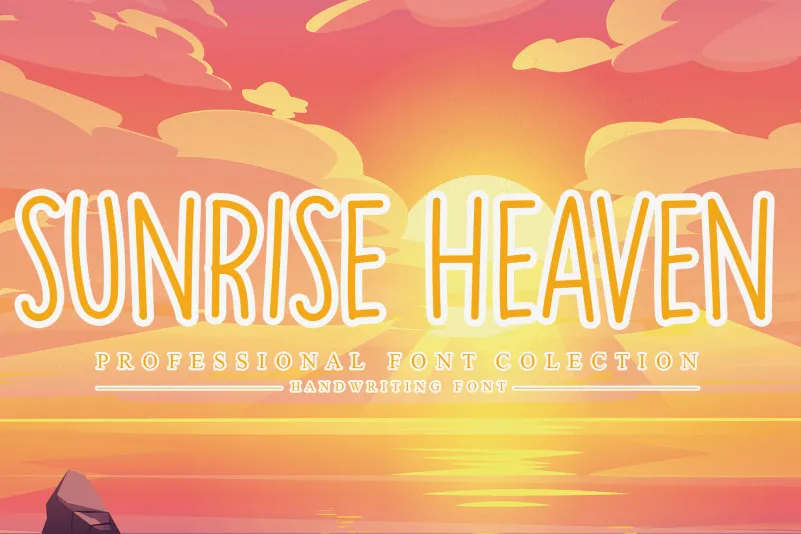
Sunrise Heaven Display Font – Fonte Grátis
Sunrise Heaven Display Font
A Sunrise Heaven Display Font é uma elegante fonte escrita a mão que se destaca pela sua simetria simples, finura e altura alongada. Ideal para criar designs inovadores em qualquer aplicação visual, desde etiquetas até logotipos, esta fonte tem como base uma linguagem fluida e delicada, perfeitamente adaptada para ambientes criativos que valorizam personalidade e sofisticação. Suave mas assertiva, Sunrise Heaven Display é uma escolha perfeita para quem busca entregar um toque único em qualquer projeto visual de rótulo ou impressão em grande escala. Com seu design cuidadosamente elaborado por andikastudio, a fonte oferece uma ferramenta versátil e de alta qualidade para designers que buscam expressar sua personalidade através do tipo.